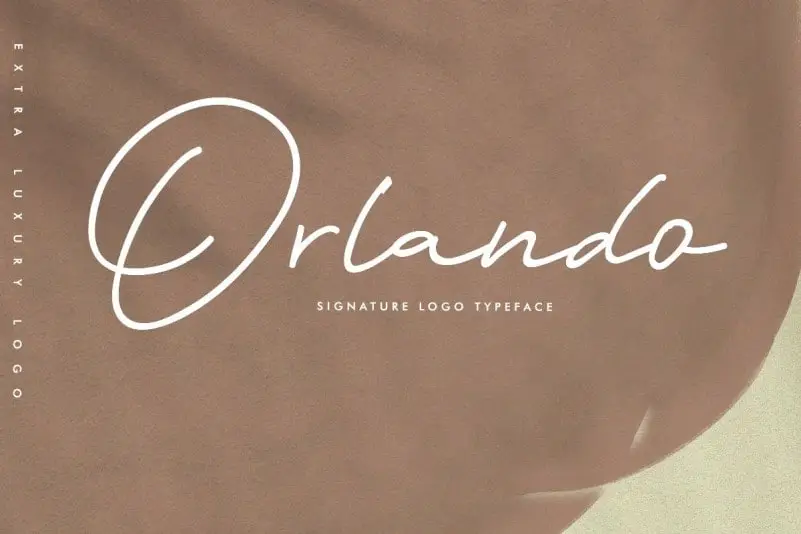
Orlando Signature Script Font – Download Grátis
A Orlando Signature Script Font é uma elegante tipografia cíliada perfeita para diversos projetos de logotipos e tipografia. Criada pelo font designer Anxiety Studio, essa fonte destaca-se por sua única linha que intensifica ainda mais a impressão e o interesse do projeto. Além disso, a Orlanda Signature conta com alternativas e ligatura, permitindo uma personalização ainda mais avançada, tornando cada trabalho único e distintivo. Seja para criações de logotipos memoráveis ou projetos de design tipográfico complexo, essa fonte trará um toque refinado e autêntico à sua identidade visual.